#1 영국 타이포그래피 기행 London Typography Tour ②
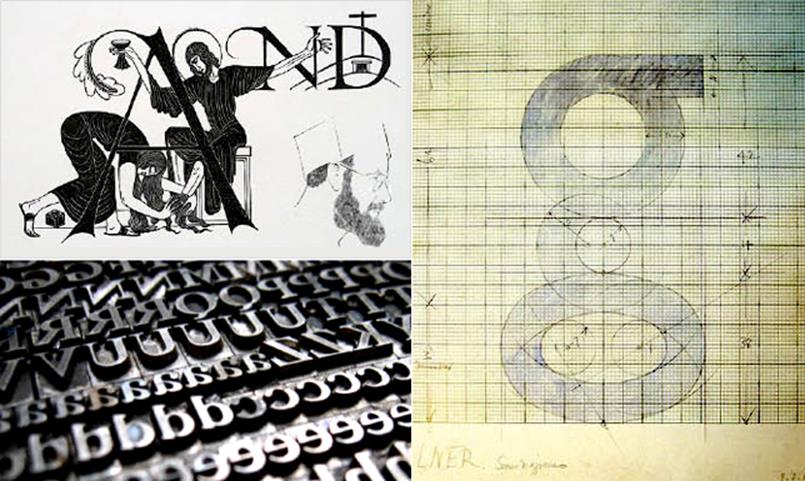
▲ 좌측은 Eric Gill의 일러스트와 활자, 우측은 그의 Gill Sans체의 작도 그리드를 보여 주는 원본 스케치
19세기가 영국 타이포그래피의 전성기였다면, 20세기는 미국을 중심으로 다른 유럽국가의 새로운 도약을 의미한다. 세계 1차대전이 발발하면서 타이포그래피와 인쇄출판 분야도 주춤하게 되었는데 1910년 이후로 미국이 이 분야에 새로운 발전국가로 떠오르기 시작하였다. Frederic William Goudy는 100여 개가 넘는 서체를 개발하였으며 Trajan과 Goudy Modern은 그 성공적이 사례로 꼽힌다. 그는 Typographica와 Ars Typographica라는 저널을 통하여 자신의 디자인 철학과 이론을 피력하였고 Elements of Lettering과 The Alphabet이라는 책을 출간하기도 하였다.
Eric Gill는 또 다른 영국 서체 디자인의 전환기를 예고하는 중요한 영국을 대표하는 타입디자이너이지만 조각가, 그리고 삽화가로 왕성한 활동을 한 다재 다능한 예술인이었다. 재미있는 사실은 그의 이러한 천부적인 재능과 방대한 작업의 이면에는 그의 독특한 종교관과 다소 엽기적인 에로티시즘의 영향이 있었다는 후문이다. 그는 런던 지하철의 전용서체를 디자인한 유명한 서체디자이너 Edward Johnston의 제자로도 잘 알려졌다. 1928년에는 유명한 Gill Sans체를 완성하였고 바로 이점이 그의 서체가 자신 스승의 영향을 받은 증거로 볼 수 있다. 그의 Sans Serif체 연구의 성과물들은 후대에 다양하게 타이포그래피와 그래픽 인포메이션 전반에 영향을 주었으며 20세기 새로운 서체 미학에 시발점이 되었다.
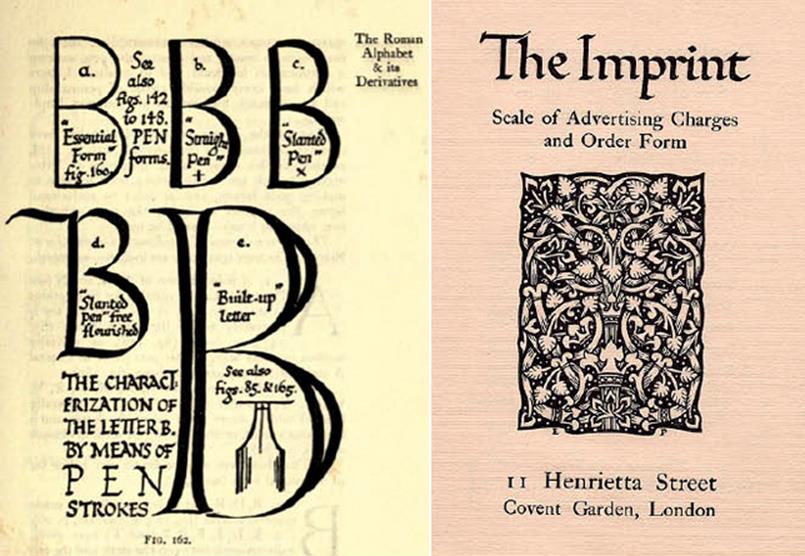
▲ 좌측은 Edward Johnston의 저술한 Writing & Illuminating, & Lettering이라는 책의 본문 중 일부. 우측은 그가 9호까지 발행했던 Imprint 잡지
세계 최초로 지하철이란 대중교통 수단을 개발 운영한 도시로서 런던은 진보적인 사고와 시스템으로 일찌감치 공공디자인의 중요성을 인지하고 이를 발전시켜왔다. 체계적인 정보디자인에 설득력 있는 광고/홍보 디자인 또한 커뮤니케이션 디자인과 미디어 발달을 촉진했다. 특히 런던지하철(London Underground: 객차와 터널의 생김새가 마치 튜브와 같다고 하여’tube’라는 애칭으로 불리 운다.)은 대표적인 예이다. Harry Beck이 디자인한 지하철역 로고와 맵 시스템은 전 세계의 지하철 도로망 맵의 원형이 될 만큼 논리적이고 함축적인 디자인으로 정평이 있다.
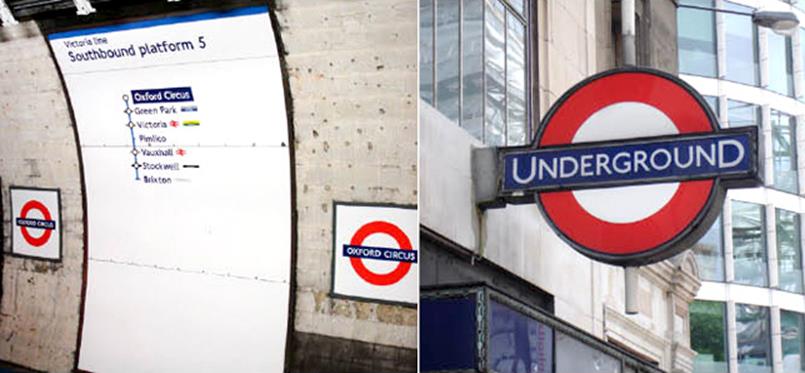
▲ 현재 사용되고 있는 런던 지하철의 로고와 승강장 플랫폼에 설치되어 있는 일부 노선도
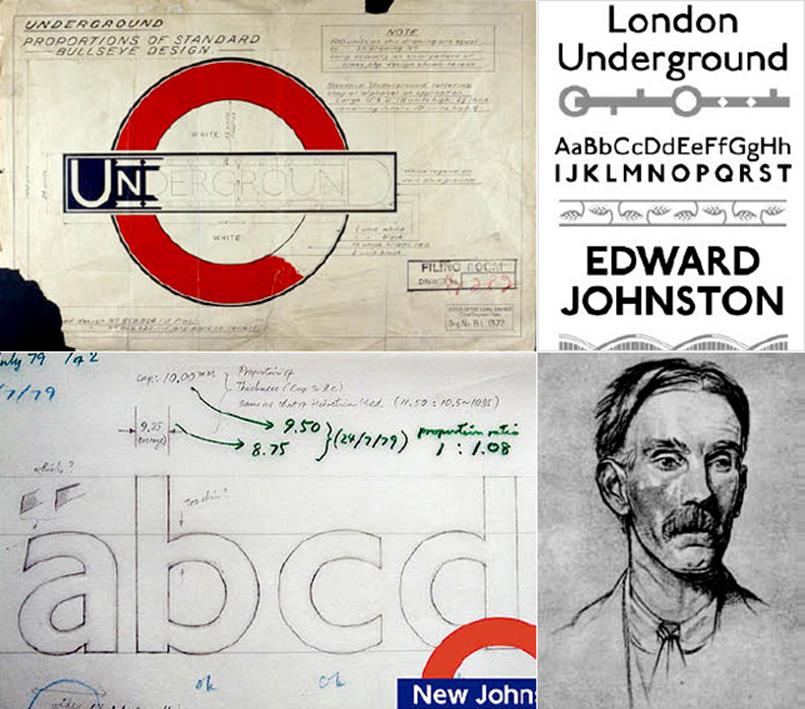
▲ 좌측 상하단의 이미지는 Edward Johnston의 런던 지하철 로고와 전용서체 스케치이며, 우측은 그 초상화.
특별히 주목할 만한 사실은 Edward Johnston (1872~1944)이라는 서체디자이너가 개발한 런던 지하철의 전용서체인’Railway Type’이다. 존슨은 원래 우루과이 태생으로 청년 시절 영국으로 이민을 와서 Edinburgh의 대학에서 의학으로 공부하고 박사 학위를 수여 받았다. 하지만 고대 캘리그라피 예술에 심취한 그는 전문적으로 서체 개발에 몰두하게 되었고 The Imprint라는 서체와 프린트관련 전문 잡지를 창간하고 9편을 편집, 발행하였다. 이후 Royal College of Art에서 1940년까지 교수로 재직하였으며 많은 후학을 지도하였다.
우리가 Johnston 을 특별히 주목하는 것은 당시 빅토리아 시대의 장식적 서체 개념으로부터 탈피한 19세기 말에서 20세기 초로 이어지는 새로운 미래 지향적 스트림라인의 san serif 서체의 유행을 예고하는 런던 지하철 아이덴티티 전용서체인”Railway type” 제작을 하였기 때문이었다. 이 서체는 가로와 세로 획의 긁기가 일정하며 기하학적인 단순미와 단단함이 돋보여 새로운 교통수단임 지하철에 대한 이용객들에 신뢰감을 주고 먼 거리와 이동 중에도 신속 정확하게 인지할 수 있는 조형적 완성도가 높은 서체로 평가 받는다.
그러나 참 아이러니한 것은 대문자와 소문자의 조합 (주로 소문자 위주로 표현된)으로 만들어진 Johnston의 교통사인 서체와는 달리 미국과 다른 나라에서 60년대 이후 대문자로만 된 사인서체 조합을 사용했다는 것이다. 많은 사람이 대문자로만 된 지명이나 문장이 가독율이나 변별력, 그리고 주목성이 더 높다고 생각했기 때문이다. 하지만 90년대 이후부터 최근에 이르러 다시 소문자 위주의 사인이 더 효과적이라는 점을 다양한 실험을 통하여 입증되었고, 바로 이 점이 Johnston의 선경지명에 놀라움을 금치 못하는 것이다. 더불어 그는’Roundel’이라는 이름의 로고를 제작하였는데 이제는 영국을 대표하는 하나의 상징물로서 지하철뿐만이 아니라 버스 등 런던의 모든 공공 교통수단에 전부 적용되어 통일감을 주는 전반적인 시각 표준화 시스템으로 사용됨은 물론이요 예술과 문화 상품으로 끊임없이 발전해 오며 많은 이에게 사랑을 받고 있다
▲ 좌측 위로부터 1923년경부터 제작된 초기 Metro Railway의 3종류의 런던 지하철 노선도로서 사실적인 지형에 근거 한 디자인이었다. 그래서 시각적으로 복잡하고 특정 구간과 밀집지역의 정보는 식별이 어렵다. 그나마 마지막 노선도는 지형물의 배경화면을 삭제함으로써 다소 간결 해져가고 있음을 보여준다. 우측 상단의 사진은 Harry Beck이 제작한 노선도의 초기아이디어 스케치이며 아래의 사진은 최종 완성된 노선도와 그 상세도이다.
▲ 영국과 스코틀랜드를 연결하는 Motorway map, 우측 상단은 초기 노선도가 조금씩 수정되어 현재 사용되고 있는 런던 지하철 노선도이며, 하단의 사진은 자신이 제작한 지도 앞에 서 있는 Harry Beck의 모습이다.
1913년 이전까지 런던의 대중교통은 여러 회사에서 나누어 운영을 하여왔었다. 혼돈된 운영체계와 노선표 등을 하나로 통합하는 아이덴티티 작업이 필요했다. London Transportation으로 명명된 이 회사는 더 많은 사람이 지하철과 버스를 이용하도록 이미지 통합 작업을 시작했다. 당시 런던 지하철 회사에서 엔지니어링 기술자로 일하던 Harry Beck은 1931년에 자신이 개발한 노선도를 디자인하여 수차례의 걸친 설득을 통해 마침내 당시로써는 혁신적인 노선표로서 공식적으로 사용이 시작되었고, 그 반응은 뜨거웠다. 물론, 여기에는 에드워드 존스턴의 시각 표준화 작업의 놀라운 힘이 밑바탕이 되었음은 두말할 필요가 없는 사실이다. 그는 실제 지리정보를 그대로 시각화할 때 생기는 문제점(실제 역과 역 사이의 간격과 일정치 않은 복잡한 루트)을 해결하며 동시에 심리적으로 더 빠르고 안정감 있게 느낄 수 있게 역 간격을 일정하게 함과 동시에 모든 루트를 수직 수평 및 45도 사선으로 표현하여 지도가 한결 단순명료 해 지도록 디자인하였다.
▲ 근래에 London Subway에 도입된 새롭고 다양한 부가서비스를 지하철 노선도의 디자인 모티브와 컨셉을 극대화하여 제작한 광고물들로 하나의 잘 만들어진 공공디자인이 얼마나 지속적이고 효과적인 커뮤니케이션과 파워를 발휘하는지를 보여주는 좋은 예들이다.
▲ 초기부터 최근까지 끊임없이 만들어지는 참신하고 효과적인 아이디어의 지하철 및 대중교통 관련 광고물
▲ 좌측은 네덜란드 디자이너이자 일러스트레이터인 Sam Loman이 London Subway 노선도와 인간의 해부학적 (마치 동맥과 정맥이 혈류의 흐름의 통로인 것과 같은 이치) 유사성을 컨셉으로 만든 Under Skin이란 작품이다. 우측 상단은 심장의 시각화한 혈관도를 컨셉으로 만든 예이며, 우측 하단의 사진은 현대 실험미술을 주로 전시하는 The Tate 갤러리를 런던 지하철의 애칭이자 미술물감 튜브를 동시에 의미하는 단어 “Tube”를 컨셉으로 상징적인 포스터를 만들었다.
▲ Penguin books의 유명한 3단 띠형식의 시리즈 표지 디자인과 심볼로고의 스케치
영국 타이포그래피에 빼 놓을 수 없는 또 다른 중요한 출판사가 바로 1935년에 Allen Lane과 V.K. Krishna Menon에 의해 설립된 저가의 제작비와 최고의 콘텐츠로 승부한 문고판 paperbacks의 대명사 Penguin books이다. 세계 2차대 전을 거쳐 전 세계적으로 인기를 얻은 그야말로 출판 타이포그래피의 중요한 업적을 남긴 출판사이다.
Penguin books 커버는 시리즈 출판물에 새로운 유행을 일으켰다. 단순한 수평 3단으로 나뉘어진 커버는 상.하단엔 시리즈의 아이덴티티 칼라 (오렌지는 일반적인 픽션물, 녹색은 범죄 사건물, 고채도 붉은색은 여행과 어드벤처물, 어두운 청색은 바이오그라피, 노랑색은 잡다한 여타의 주제물, 붉은색은 드리마, 보라색은 에세이, 그리고 회색은 월드 어페어 등의 주제를 나타낸다)를 적용하였고. 흰색부분인 가운데 공간에는 책의 타이틀과 저자의 이름이 위치한다. 당시 21살의 젊은 디자이너 Edward Young에 의하여 만들어진 커버 시리즈는 Eric Gill의 sans serif체가 적용된 간결하고 명료한 디자인으로 호평 받았다.
한편 독일에선 바우하우스를 중심으로 한 새로운 타이포그래피 운동이 일어나고 있었고 그 중심엔 Gill’s Sans Serif나 Paul Renner’s Futura 같은 간결한 Sans Serif체가 영향을 주어 다가 올 구성주의, 모튤러 시스템, 그리고 미니멀리즘을 예견하기에 이른다. 이 부분은 다음에 이어질 스위스와 독일 타이포그래피 여행에서 다시 다루기로 하겠다.
▲ 좌측은 펭귄북스의 시리즈물이며, 우측의 사진은 출판물을 이용한 홍보용 머그컵 디자인이다.
▲ Penguin Books의 75주년 기념으로 New York의 그래픽 디자이너 Amy Fleisher가 만든 해학적인 일러스트레이션
▲ 브라질의 광고대행사인 IESP의 아트디렉터이자 카피라이터인 Elias Figueiroa이 디자인 한 Penguin books의 광고물 간결한 타이포그램을 사용하여 파워풀하고 유희적인 시각 메시지가 돋보이게 만든 작품들이다.